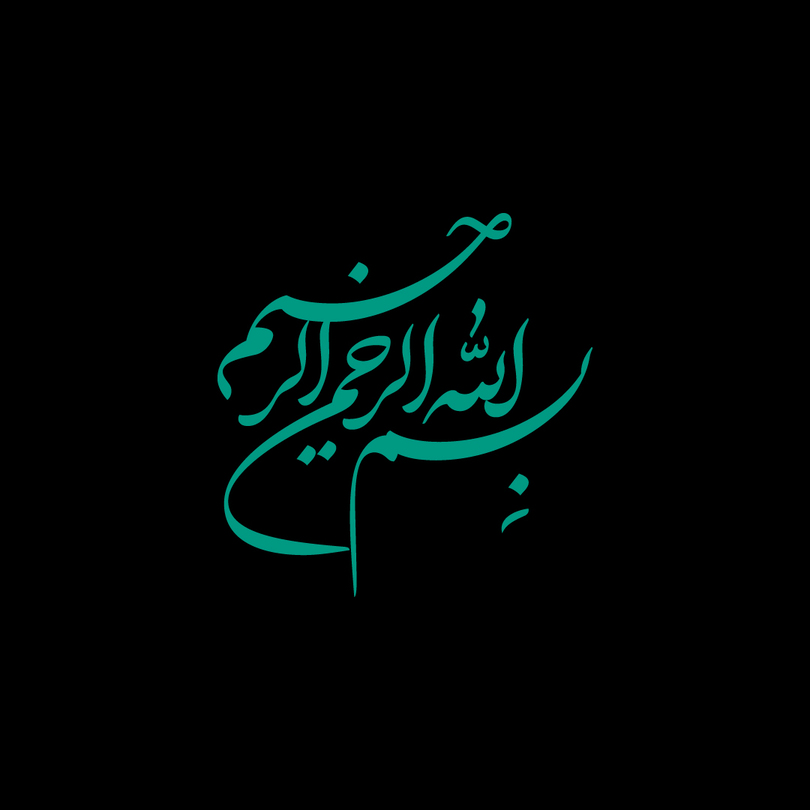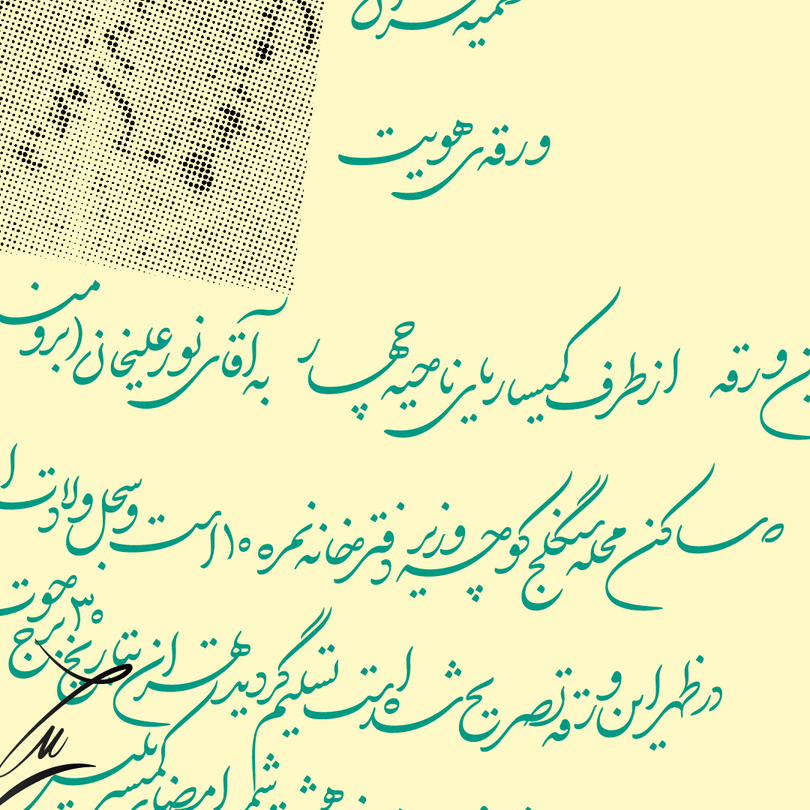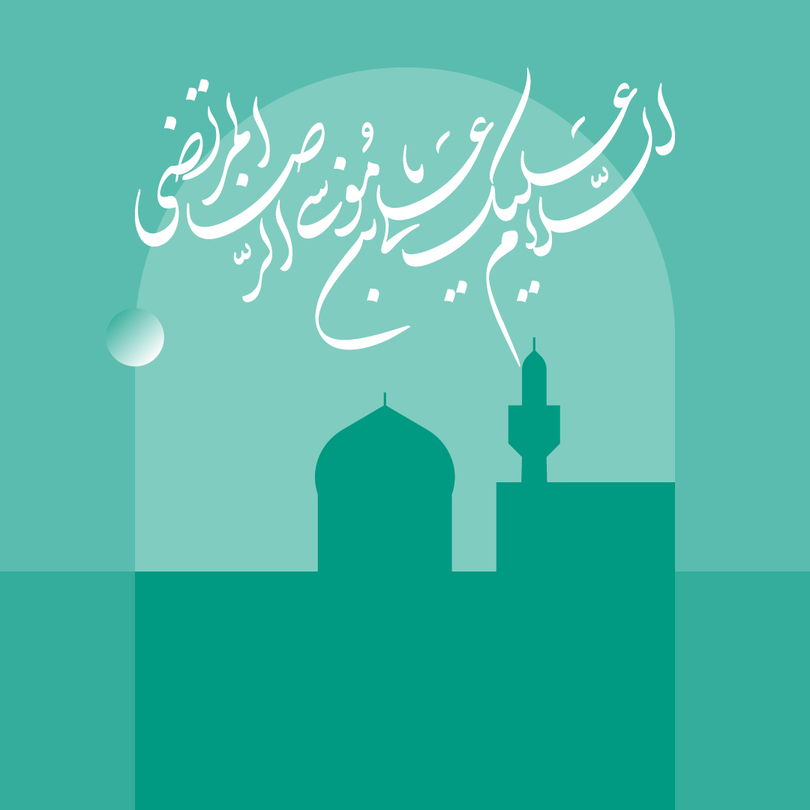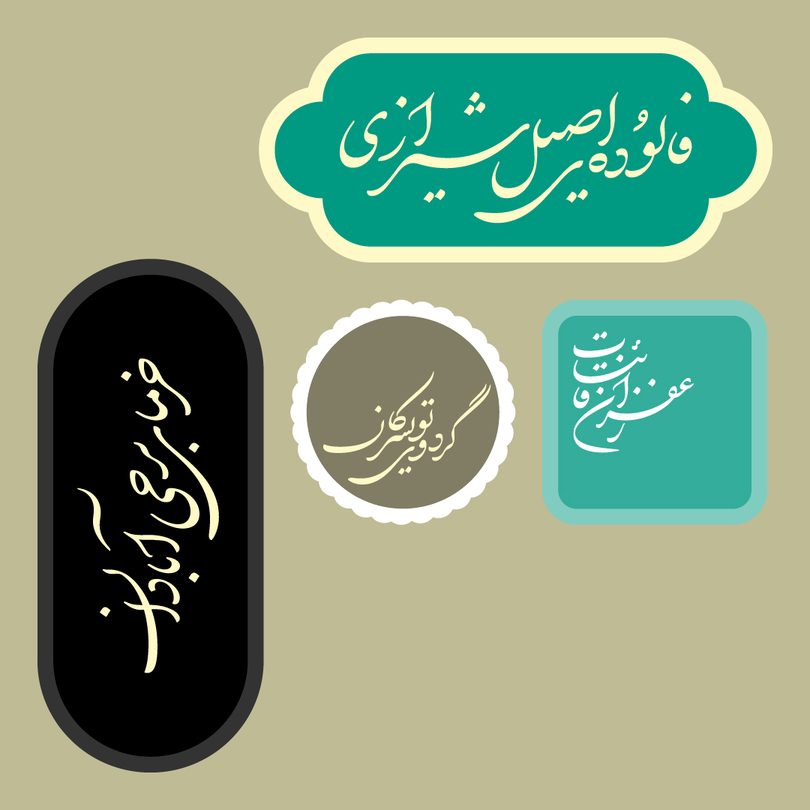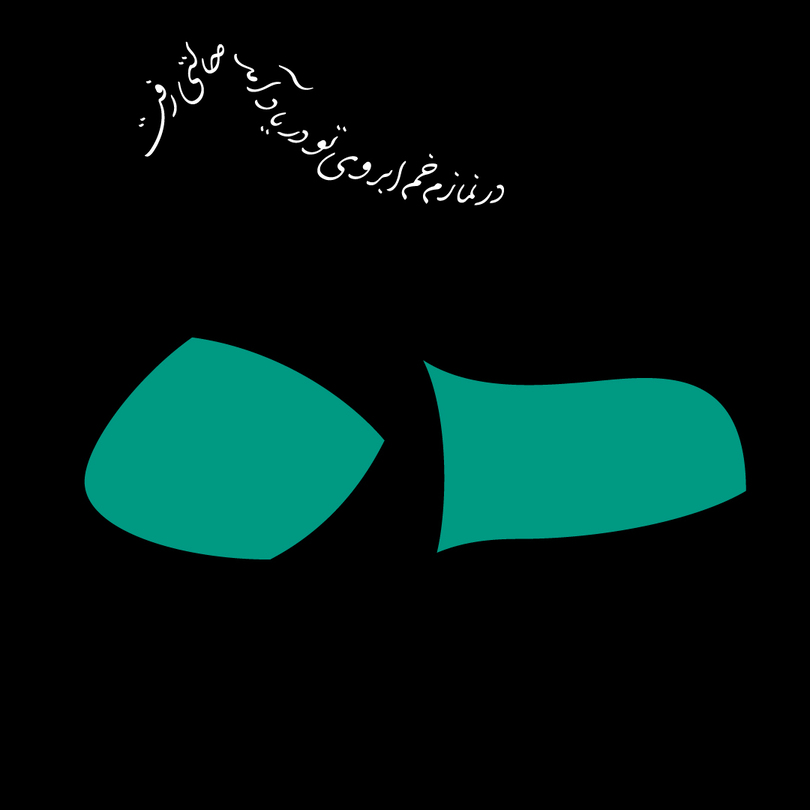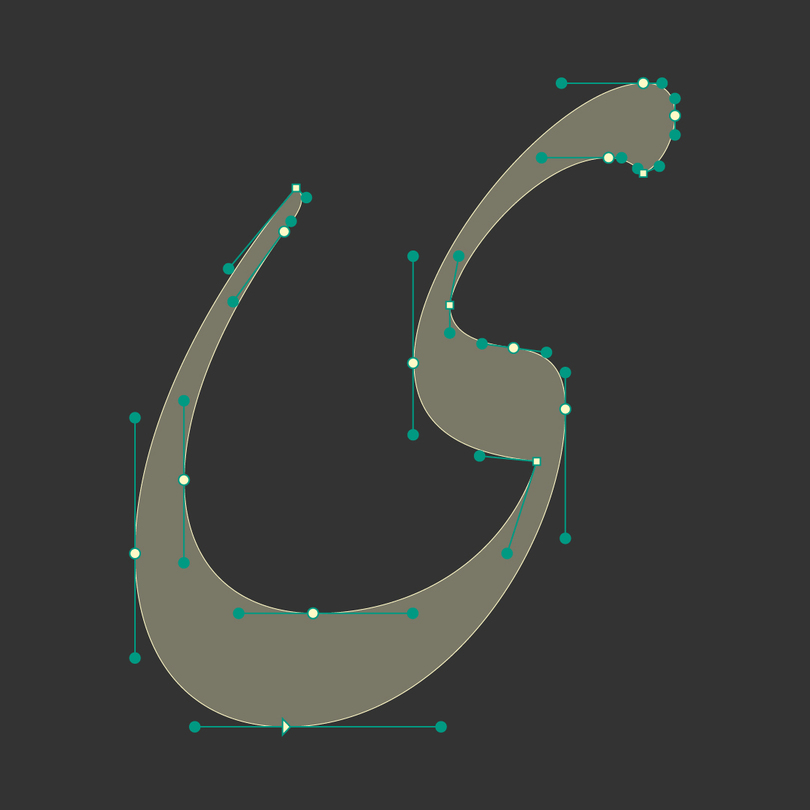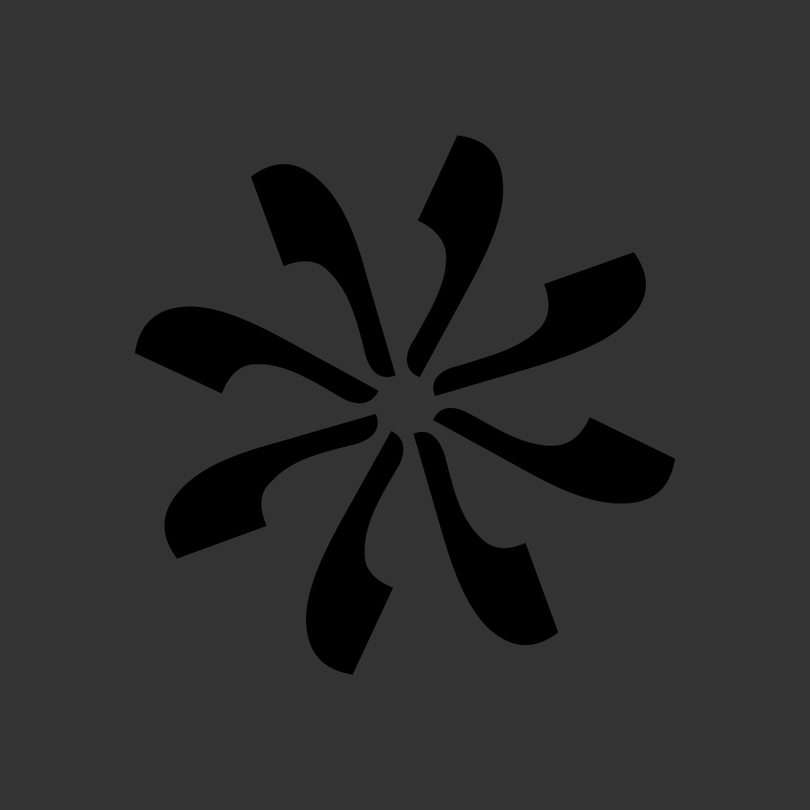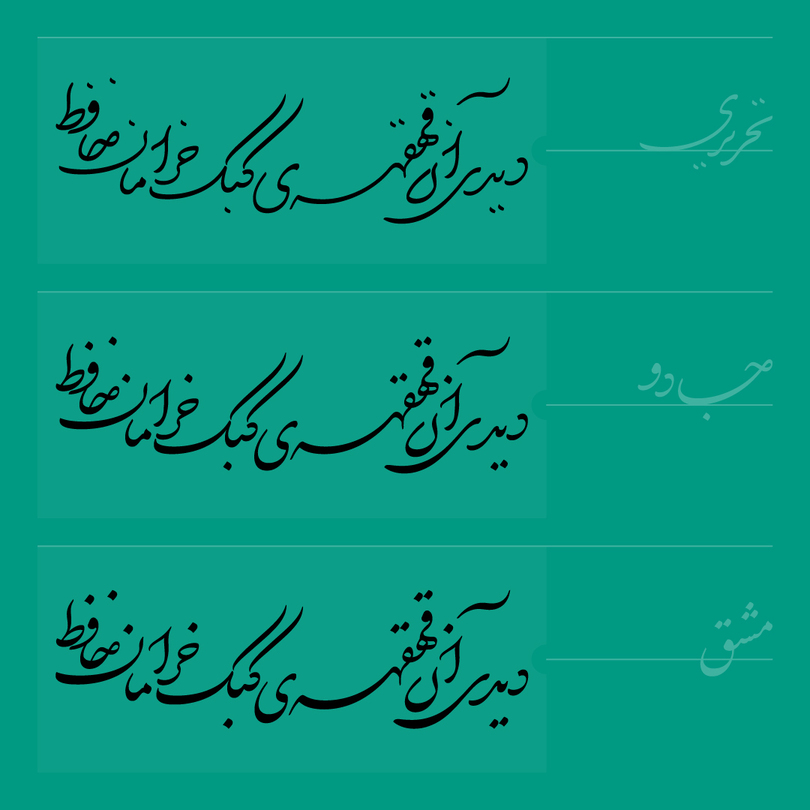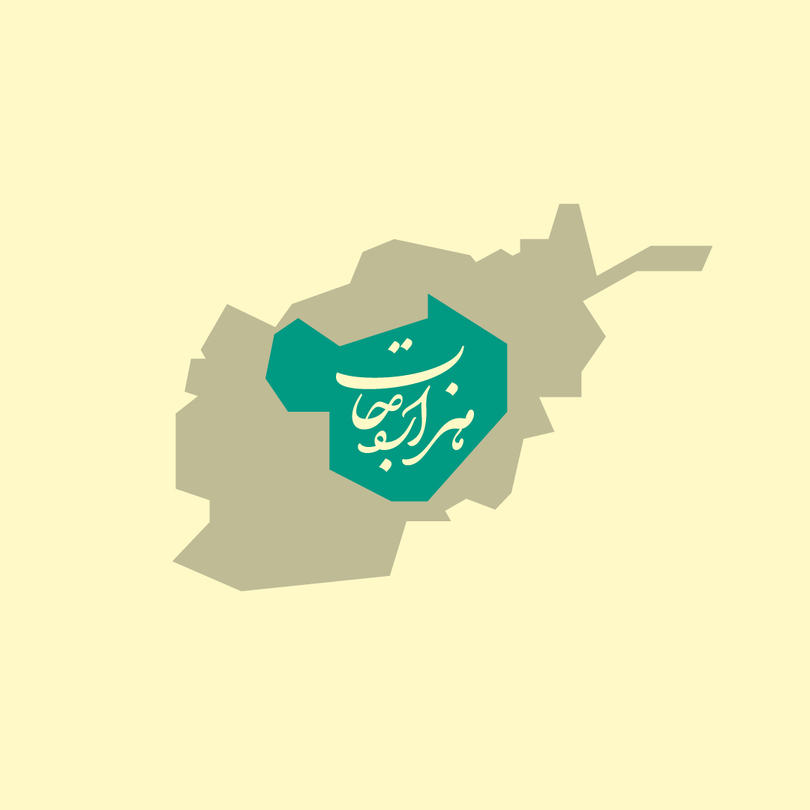
قلم دبیر font Dabir
قلم دبیر
کاری از امیر مهدی مصلحی
درباره قلم دبیر
خط شکستۀ نستعلیق انشعابی است از خط نستعلیق. یکی از تعاریف ممکن برای شکسته‌نویسی این است که شیوه‌ای از نوشتنِ یک خط مشخص است که در آن کلمات روان‌تر تحریر می‌شوند. به‌همین علت، شیوۀ شکستۀ یک خط - با توجه به دو نمونه‌خطِ شکستۀ تعلیق و شکستۀ نستعلیق - هندسۀ پیچیده‌تری نسبت به خط اصلی دارد. موارد دیگری که می‌توان در توصیف خط شکستۀ نستعلیق ذکر کرد عبارت‌اند از:
- متصل‌نویسی تعداد مشخصی از گروه‌های حرفی
- انداختن (حذف) و تسطیح دندانه‌ها
- تلخیص برخی از اجزای حروف
طراحی قلم دبیر (تحریری) در سال ۱۳۹۸ با هدف ساخت ابزاری توانا برای تحریر متن‌های ادبی-آموزشی و کاربردهای فرهنگی انجام شد. بنیان اولیۀ دبیر از کتاب ارزشمند «آموزش خط شکستۀ تحریری ساده» به تحریر و تشریح هنرمند گرامی جناب آقای عباس رحمانی شکل گرفت. در حین طراحی این قلم در نگاشته‌های ایشان جرح‌وتعدیل‌هایی صورت گرفت که لزوماً نه از حیث زیبایی‌شناسیِ خوشنویسانه که بیشتر به جهت ملاحظات فنی طراحی قلم اعمال شدند.
اینک بعد از گذشت دوسال، قلم دبیر تحریری بازطراحی و دو وزن دیگر به‌ نام‌های جادو و مشق به ‌آن افزوده شد.
فرآیند طراحی دو وزن دیگر با طراحی وزن مشق آغاز شد. دانگ* مشق در خوشنویسی ایرانی قلمی است که پهنای حدوداً ۶ میلی‌متر دارد و برای سطرنویسی معمولاً به‌ کار برده می‌شود. در وزن مشقِ قلم دبیر سعی در بازسازی ضعف‌ و قوت‌ها و نسبت‌های این دانگِ قلم شده است. طراحی یک قلم خوشنویسانه و آزاد (از حیث شیوه) از خط شکستۀ نستعلیق دشوارتر از چیزی بود که فکر می‌کردم. حُسن این کار تلاش برای رسیدن به درکی پیچیده‌تر از ضرب‌آهنگ (Rhythm) حروف فارسی بود. به بیانی دیگر، «حروف چگونه در هم‌نشینی هم‌آهنگ باشند؟».
بعد از اتمام وزن مشق، به‌کمک نرم‌افزارْ از میانۀ ضخامت دبیر تحریری و دبیر مشق وزن «جادو» را طراحی کردم و با اعمال تغییراتی مختصر به دیگر قلم‌های دبیر افزودم. جادو دانگ قلمی است بین کتابت و مشق، که برای قالب چلیپانویسی در خط نستعلیق کاربرد دارد.
در خاتمه لازم به ذکر است که قلم دبیر نسخه‌ای اصیل از خط شکستۀ نستعلیق نیست (برخلاف چیزی که در طراحی قلم میرزا در مورد شیوۀ به‌خصوص خط میرزا غلام‌رضا اصفهانی جست‌وجو می‌کردم)، بل ساده‌شدۀ این خط برای مصارف عمومی و روزآمد است. بنابراین، حضورِ طراحانه‌ام در این قلم نسبت به قلم میرزا بیشتر است.
*دانگ یا دُنگ واحد اندازه‌گیری پهنای قلم و برابر با یک نقطه است.